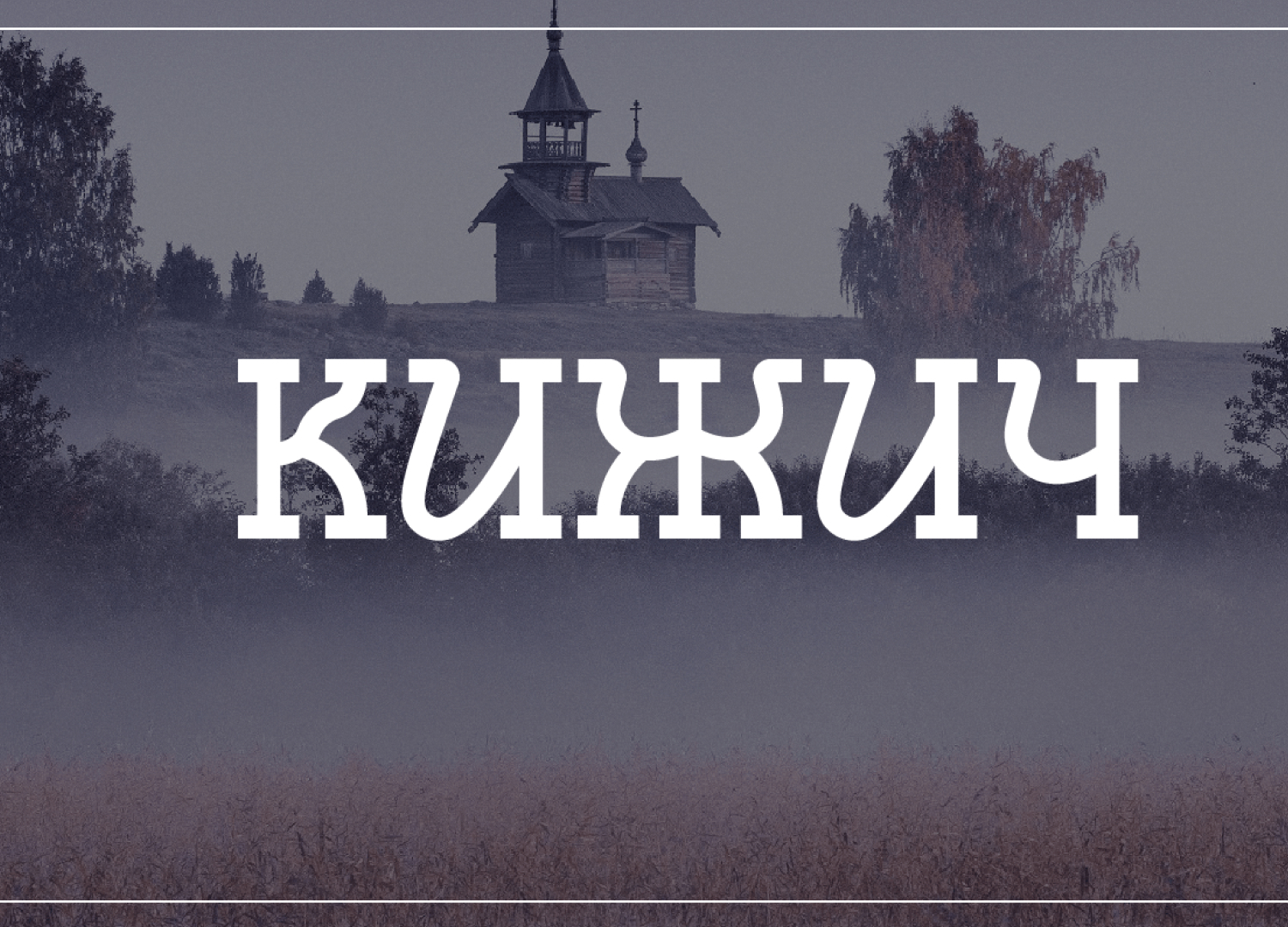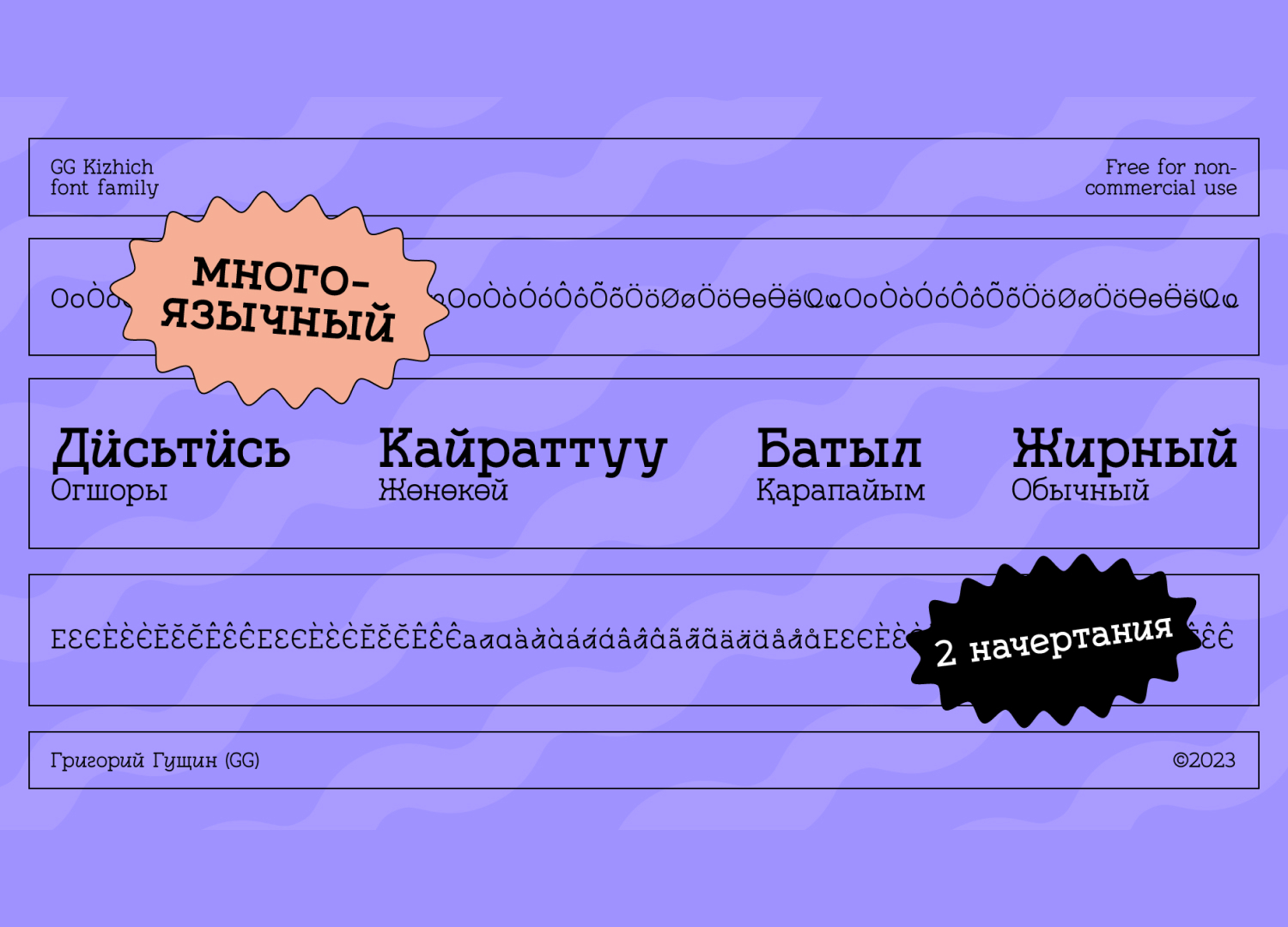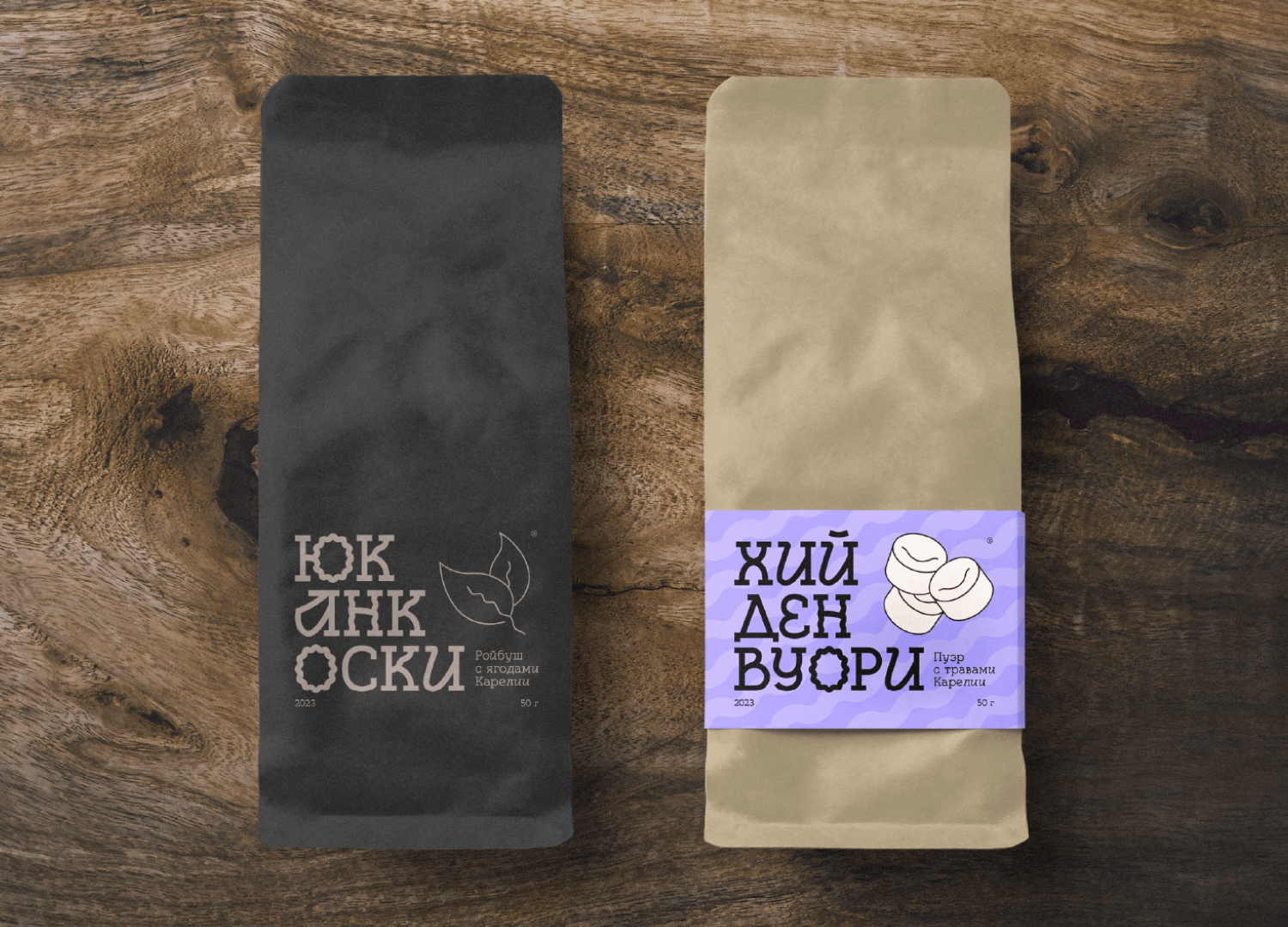
Шрифт кижич. Кириллица
Необычный шрифт с заческами. Хорош впишется в темы путешествий, музеев, и другой исторической суеты) Шрифт имеет тонкое и жирное начертание. Бесплатно для персонального использования. Автор: Grigorij Gushchin